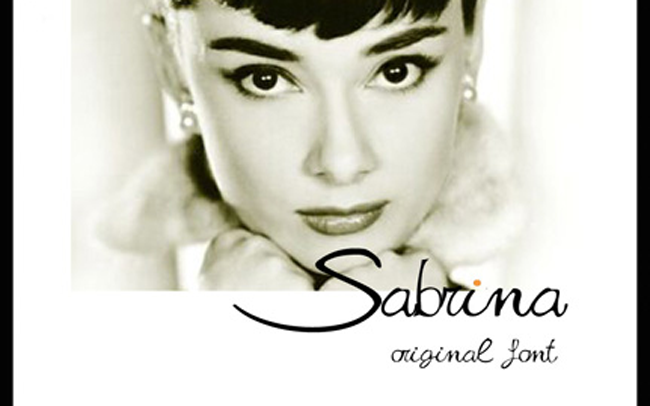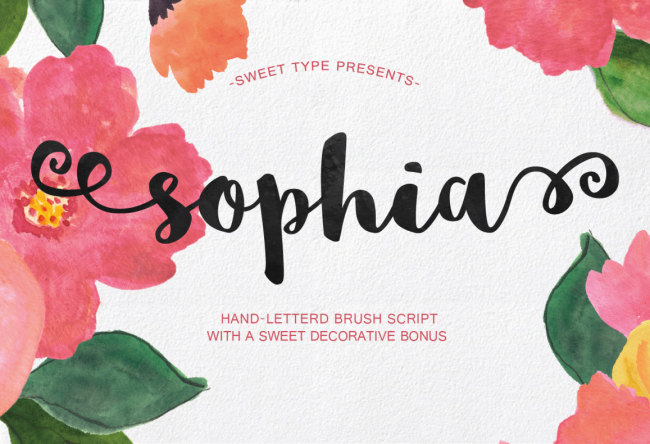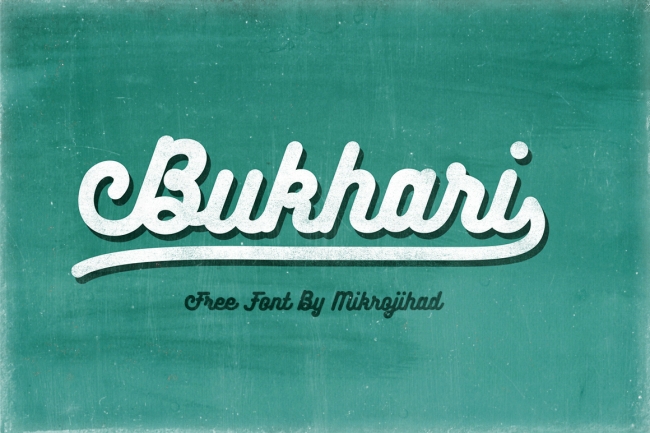
新しくリリースされたものを中心に、無料でダウンロードできる人気の筆記体フォントを集めました。
筆記体フォントはビジュアルデザインやバナーデザインなど、様々な場面で使えます。お気に入りのフォントをいくつかストックしておくと、デザインの幅が広がります。
フリーフォントの中でも筆記体フォントは種類が豊富で、高品質なものが揃っています。
筆記体は英語ではScript Font(スクリプトフォント)と呼ばれ、手書きによる流れるような、美しいデザインが特徴です。
フリーの筆記体フォント
1. Gardenia Script
Gardenia Script
美しく、楽しい印象の日一期待フォントです。春のイメージのデザインによく合います。
2. Serendipity Script Free Font
Serendipity Script Free Font
3. Arabella Free Font
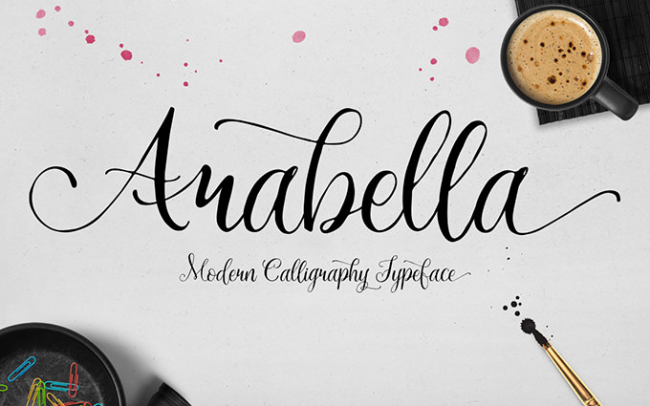
Arabella Free Font
Webやプロダクトデザインに使える、高品質な無料筆記体フォントです。
4. Grandymaa Typeface
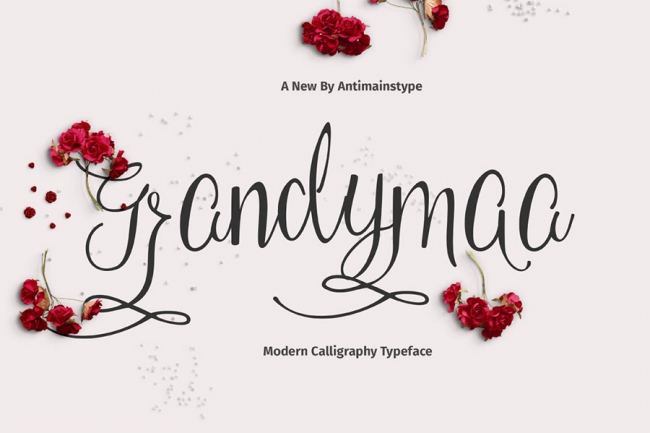
Grandymaa Typeface
甘い感じのするすてきな筆記体フォントです。ベールラインがダンスを踊るように上下しています。
5. Mi Teiyng Script Free Font
Mi Teiyng Script Free Font
伝統的な手書き文字にインスプレーションを得た、オールドタイプの筆記体フォントです。
6. Soljik Dambaek
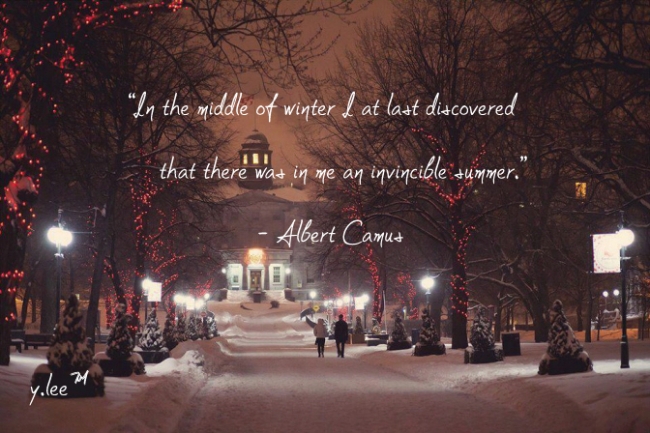
Soljik Dambaek
ちまっとした、手紙に使われるような筆記体フォントです。
7. League Script Number One
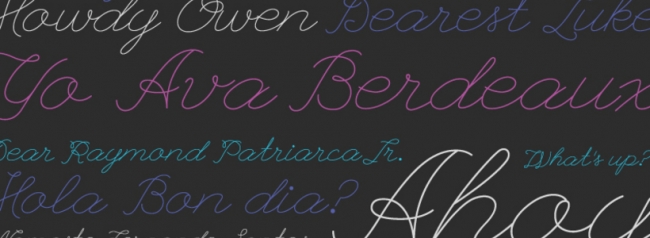
League Script Number One
若者らしい、細字の筆記体フォントです。
8. Debby Free Font
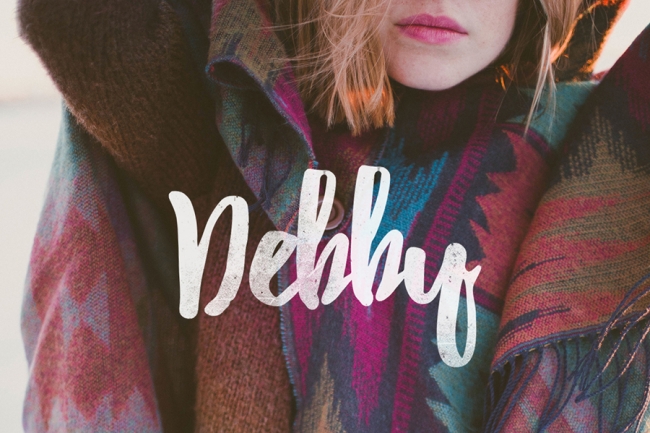
Debby Free Font
とても自然な印象を受ける、手描きのブラシフォントです。写真に重ねたり、幅広い場面で使えます。
9. Selima Script
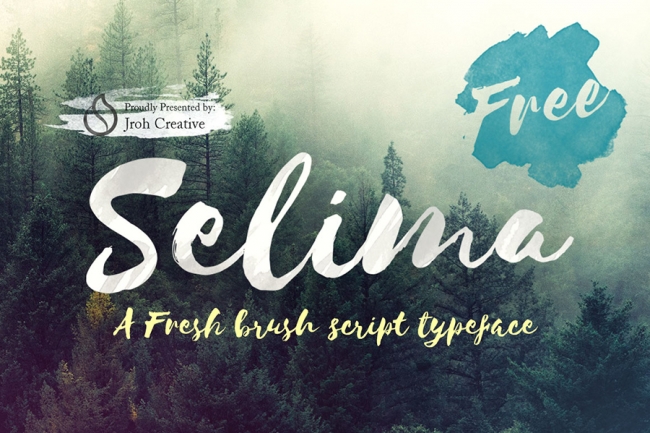
Selima Script
イレギュラーなバランス感が素敵な筆記体フォントです。アイキャッチ画像などに使えます。
10. Mightype Free Handlettered Script Font
Mightype Free Handlettered Script Font
11. Southpaw
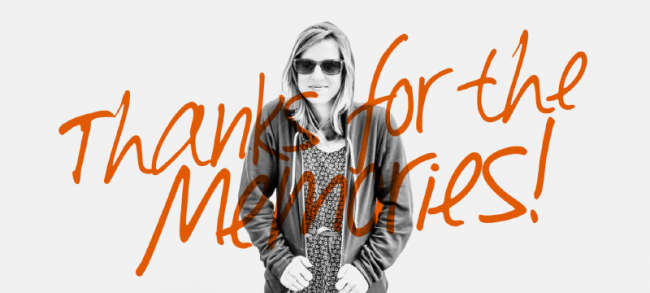
Southpaw